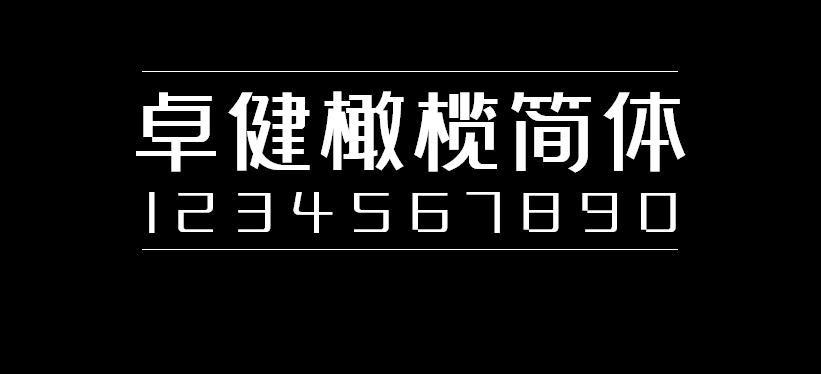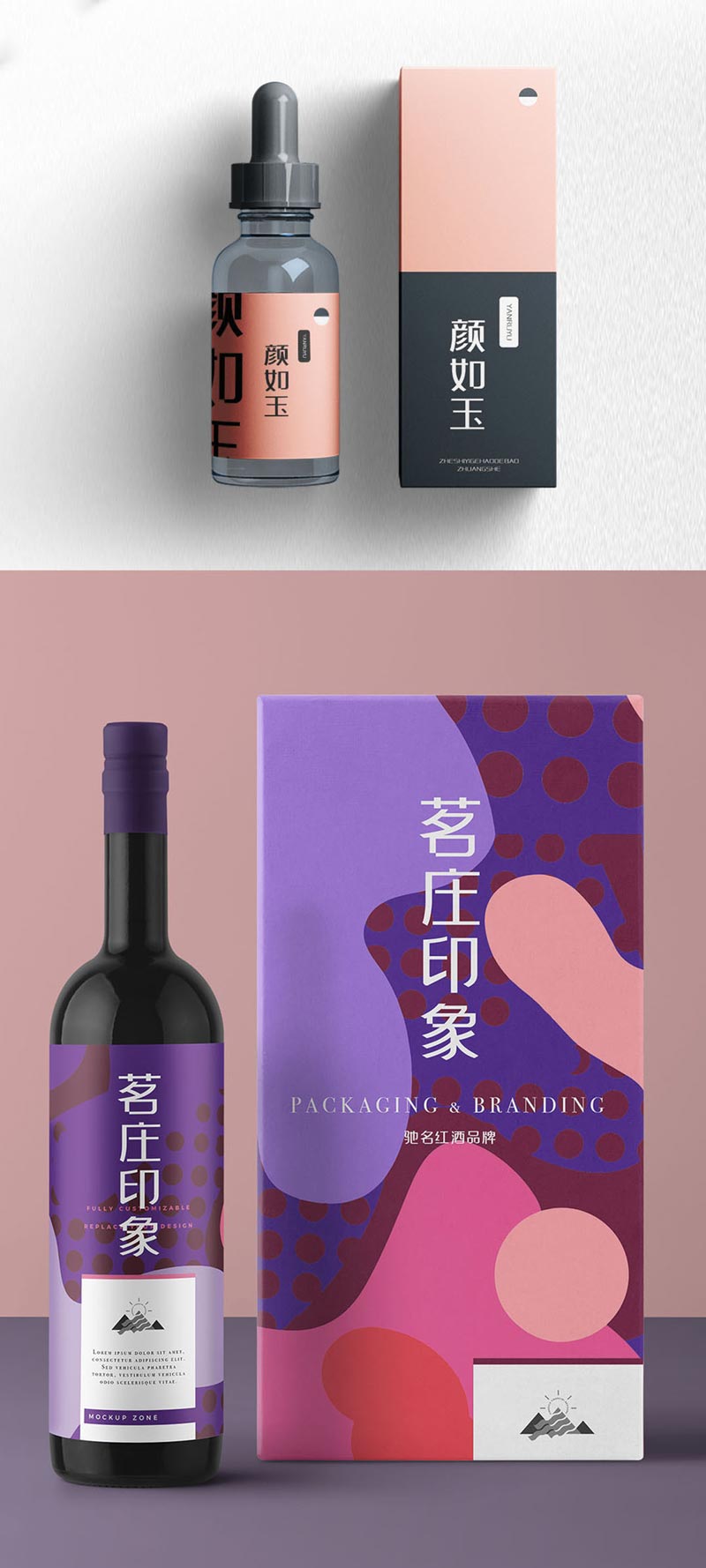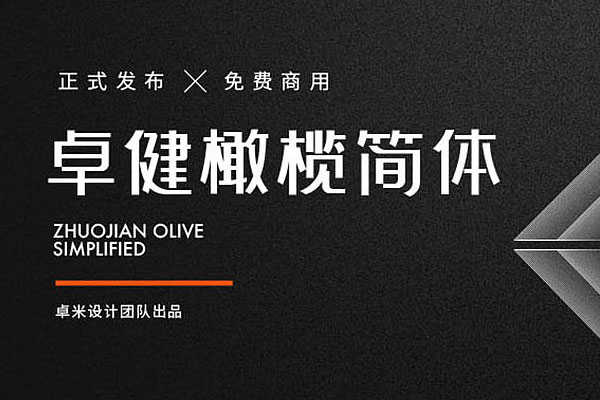
卓健橄榄简体
在2019年11月11日,在这个大家都忙着剁手的日子里,卓米设计团队却给各大设计师送上了重磅大礼,免费商用的中文字体卓健橄榄简体。2018在初,卓米设计部平面小组启动公司首套字库设计,历时1年,于2019年初完成初肯字库的设计,共计7050个中文汉字,52个英文字母,139个阿拉伯数字及常用标点符号。从调研到定位,再到草图,规范,到最后的成稿,天才知道他们团队经历多少的困难与磨合,才让这套卓健橄榄简体面世。最重要的是免费商用!免费商用!免费商用! 卓健橄榄简体是一款相对较时尚的字体,部分笔画的斜切处理,也让字体更具设计感和时尚属性,整体中心是偏上一点,更符合现代审美。字体圆角设计,让整个字体更加圆润,富亲和力。口字结构,左下角留白,个性化处理更具特色。字体斜切32度处理,让字体更有设计感更时尚。卓健橄榄简体可适用于多个行业,包括医疗、互联网、时尚等行业。